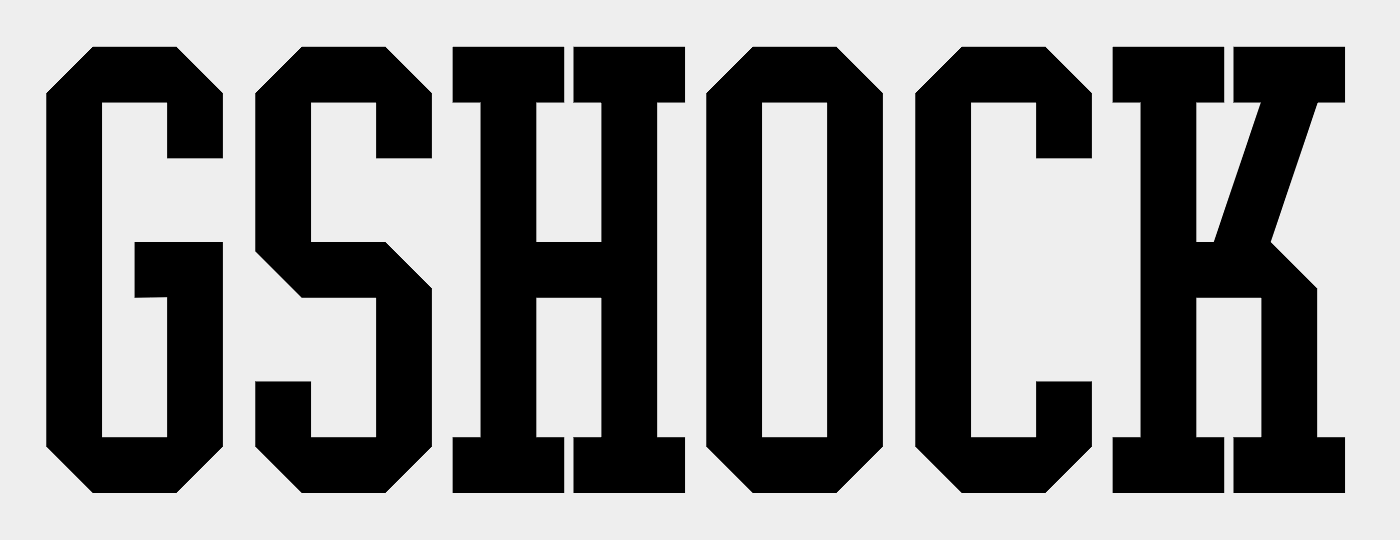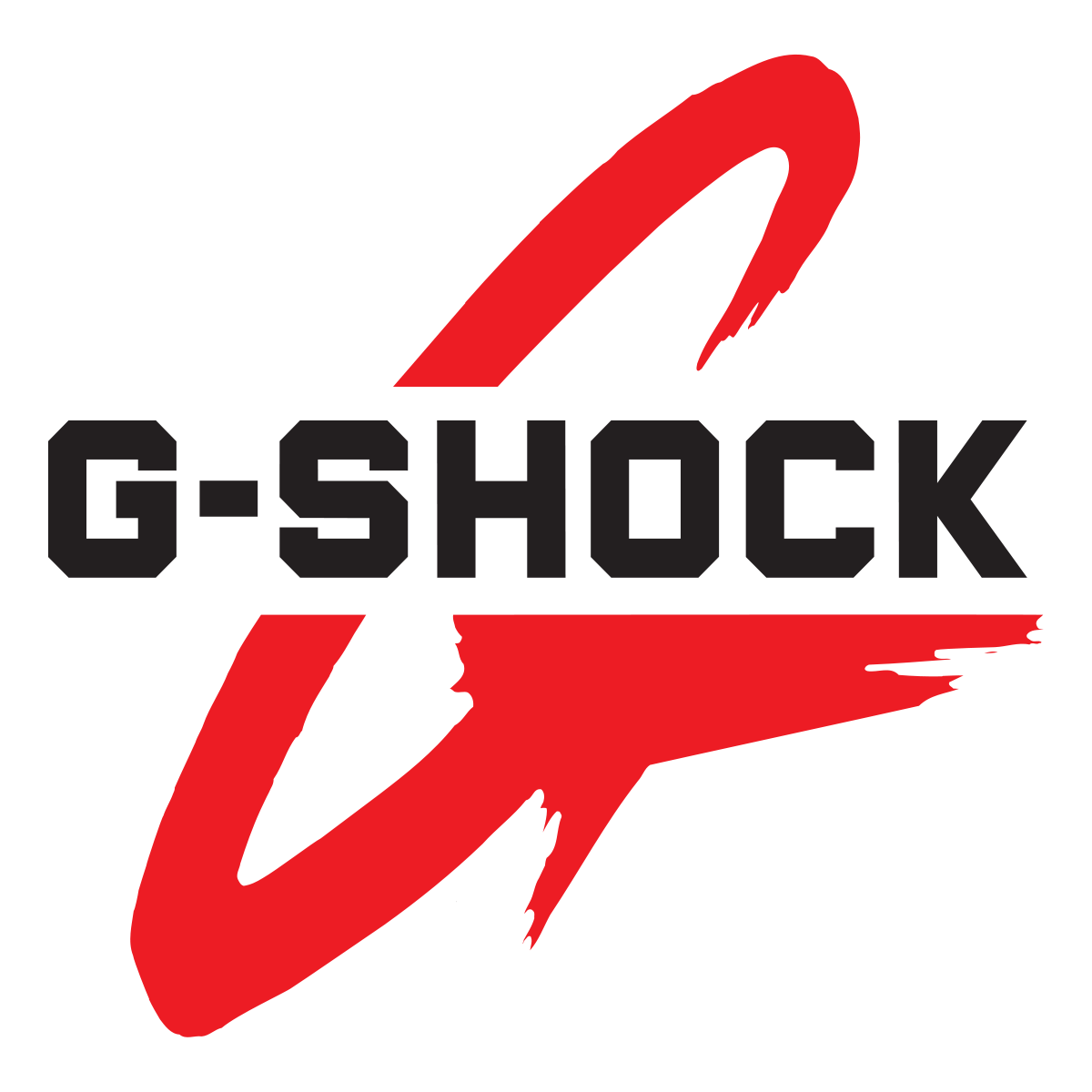
Suche Schrift der Casio G-Schock anzeige
ich suche die Schriftart des G-Schock Logos oder eine ähnliche Schriftart am Besten Kostenlos da ich sie für ein Schulprojekt benötige.
diese Art der Schriften nennt man idR "College" in Anlehnung an die Trikots der Schulmanschaften aus Gringolandia. Diese Schriften sind sehr einfach konstruiert. Daher ist es durchaus möglich, das die Buchstaben handgeblasene und mundgemalte Einzelanfertigungen sind. Da musst Du möglicherweise auch selber Hand anlegen, ggf. aber mit einer passenden Vorlage.
Bei Dafont findet man diese Schriften unter High School:
Und hier kannst Du Dir einfach mal alles aus der Rubrik  anzeigen lassen:
Hier mal drei Beinahetreffer:
Schriftenhörnchen sagt dazu: Fonts tagged “collegiate”
Hier ist die Auswahl aber weniger ergiebig: